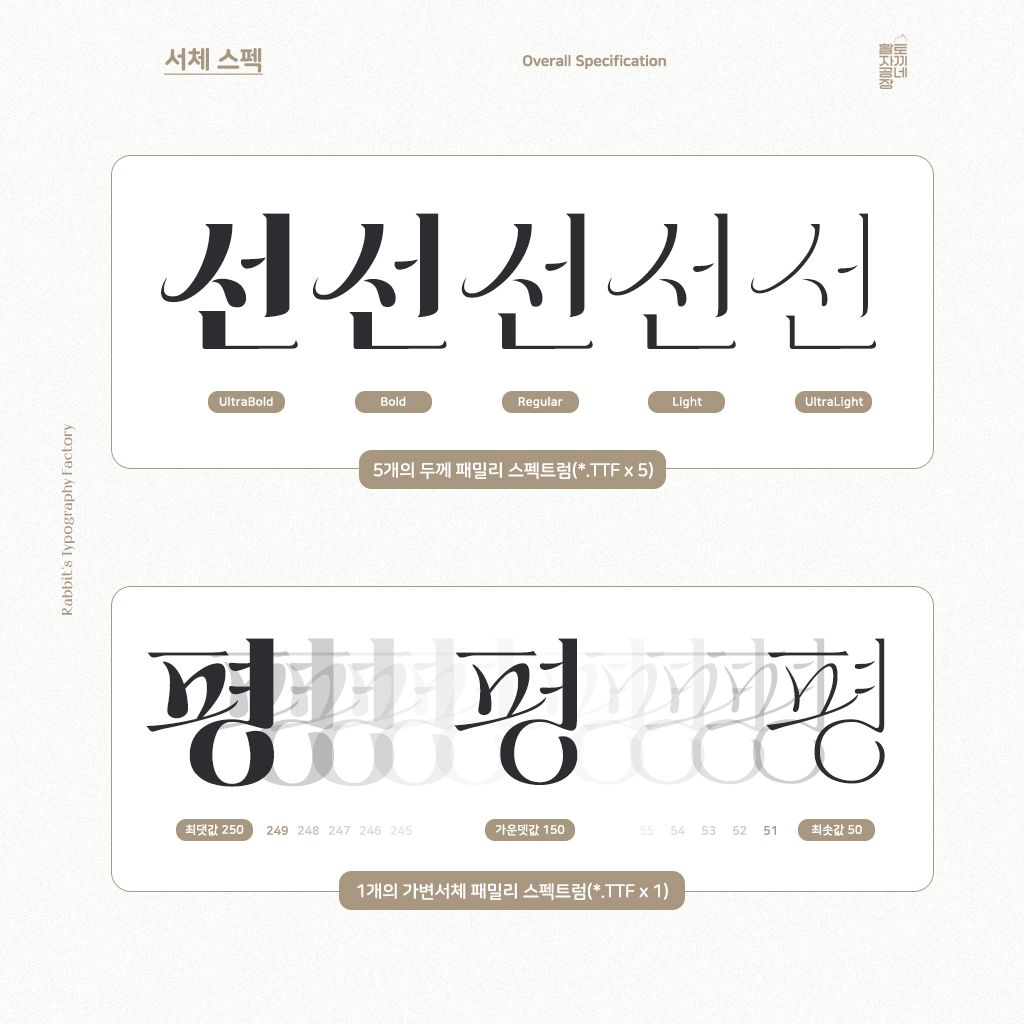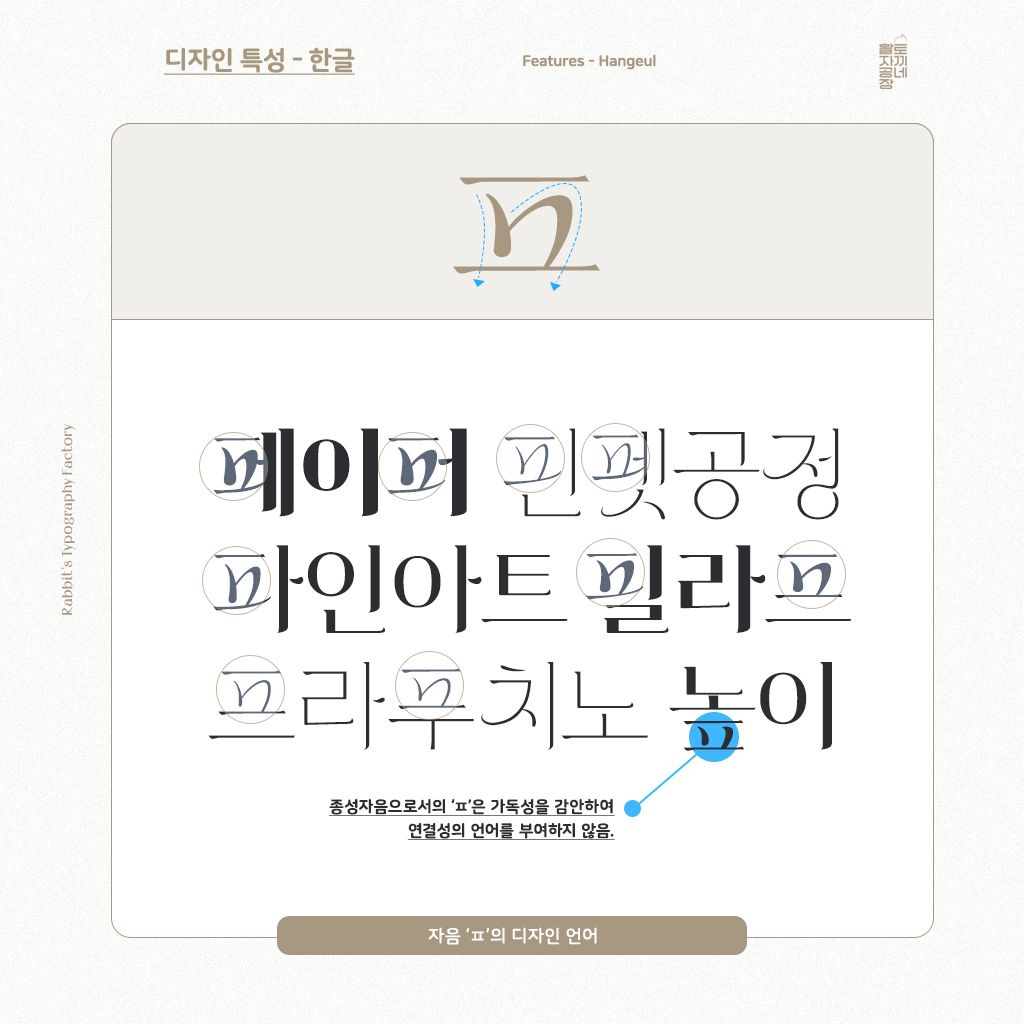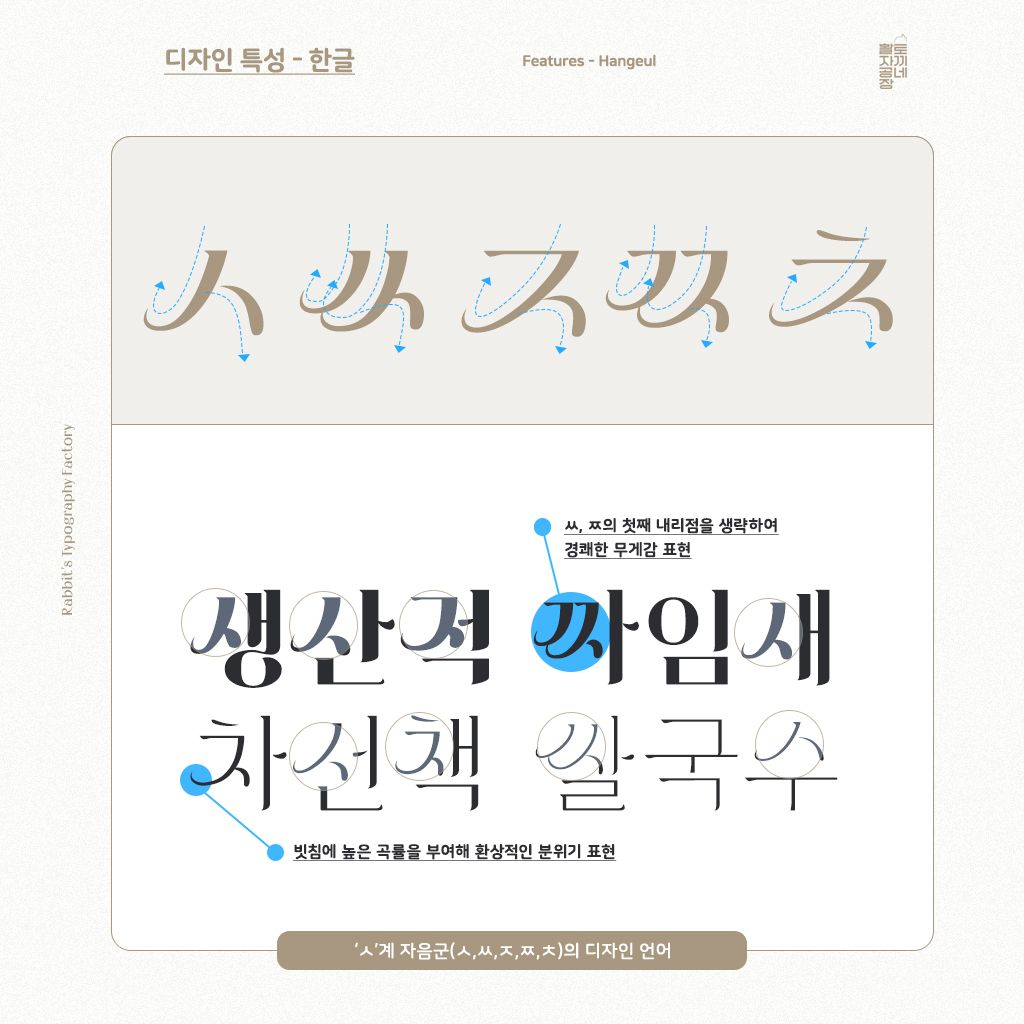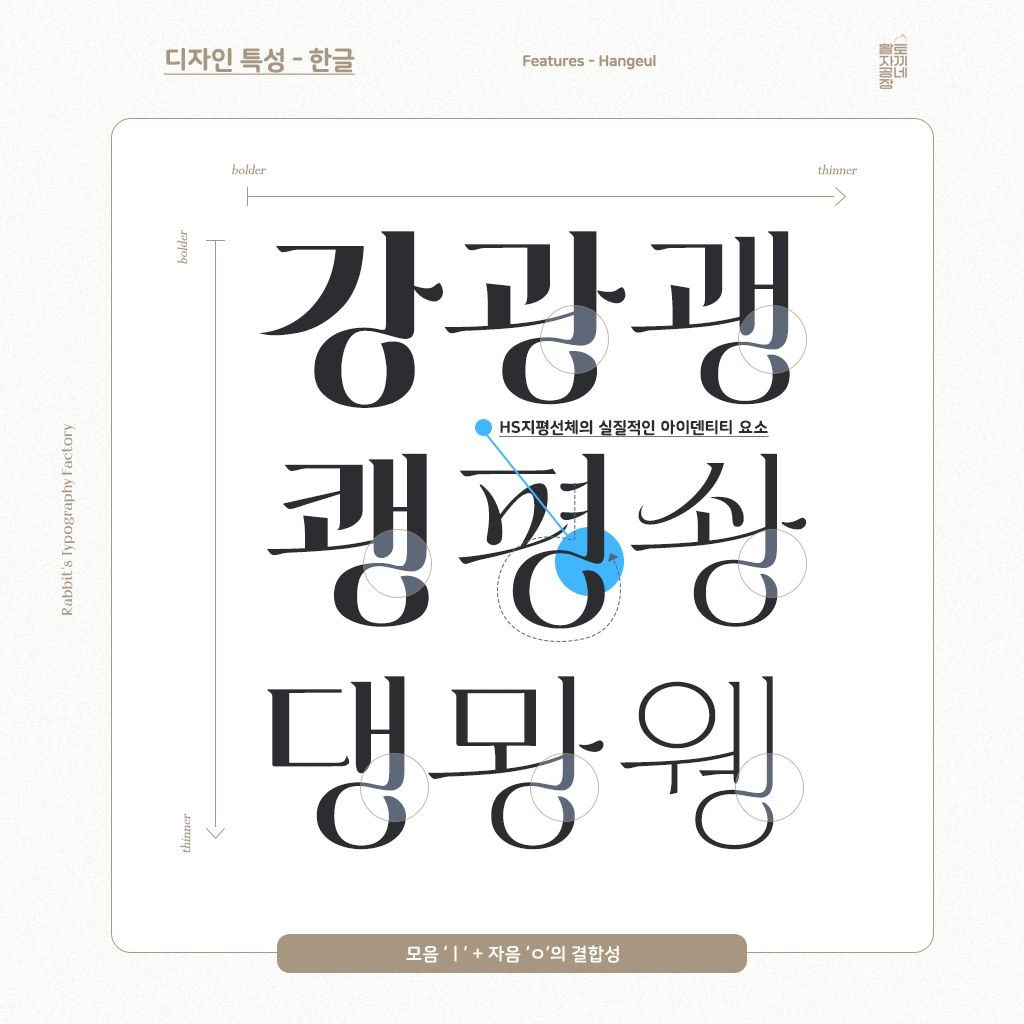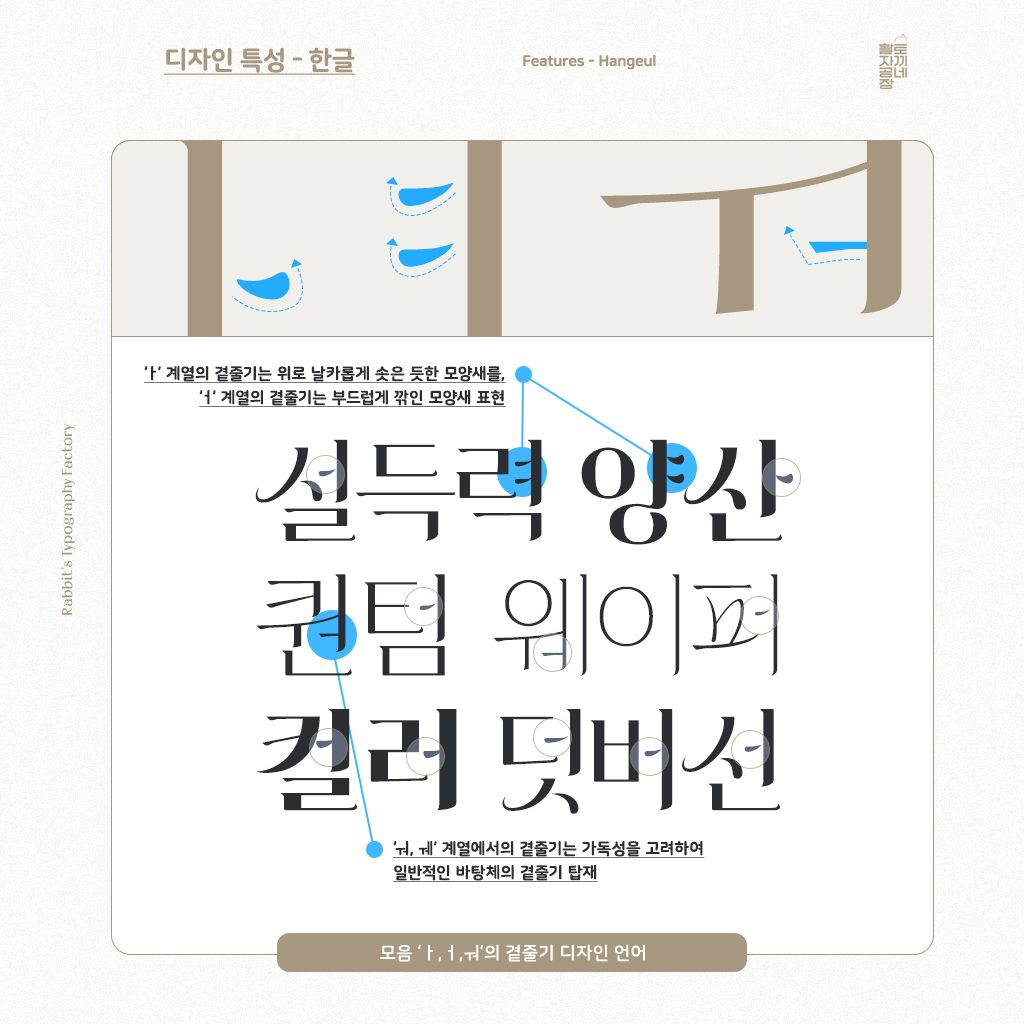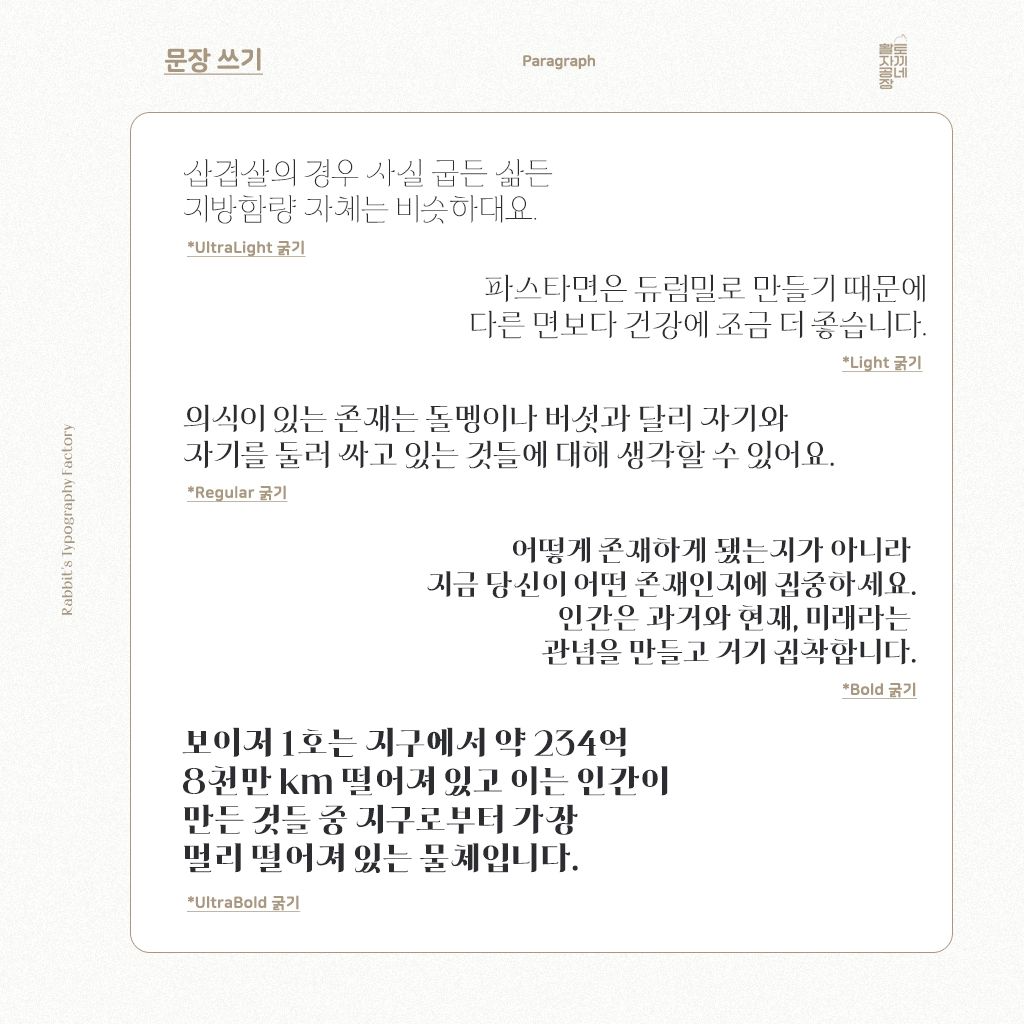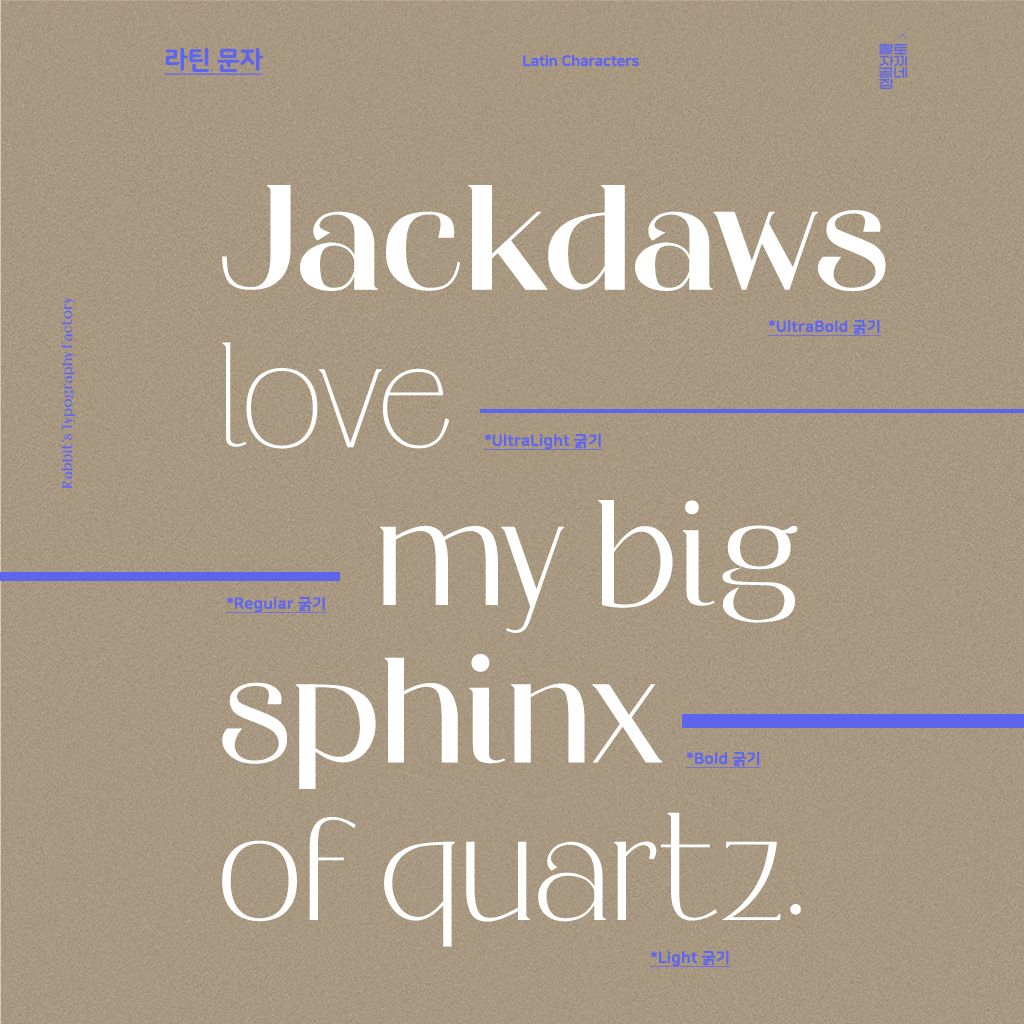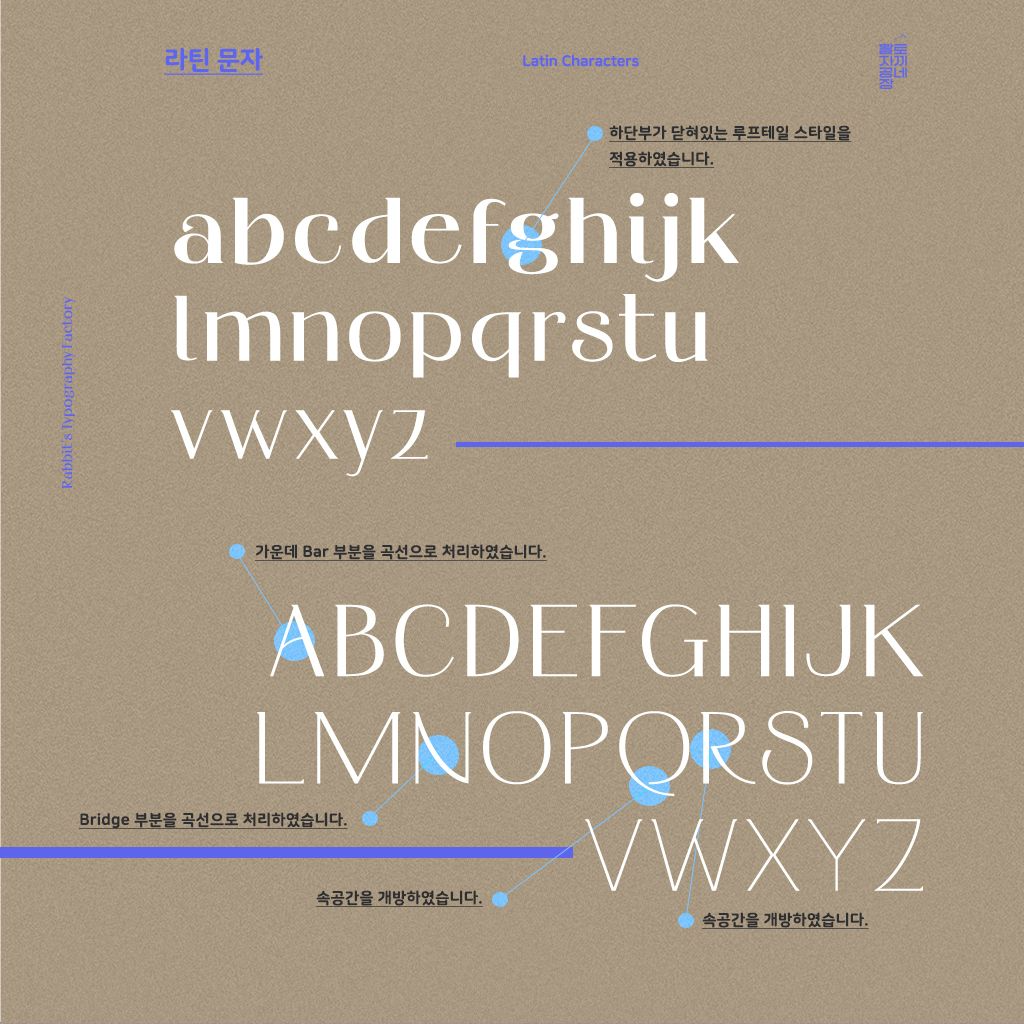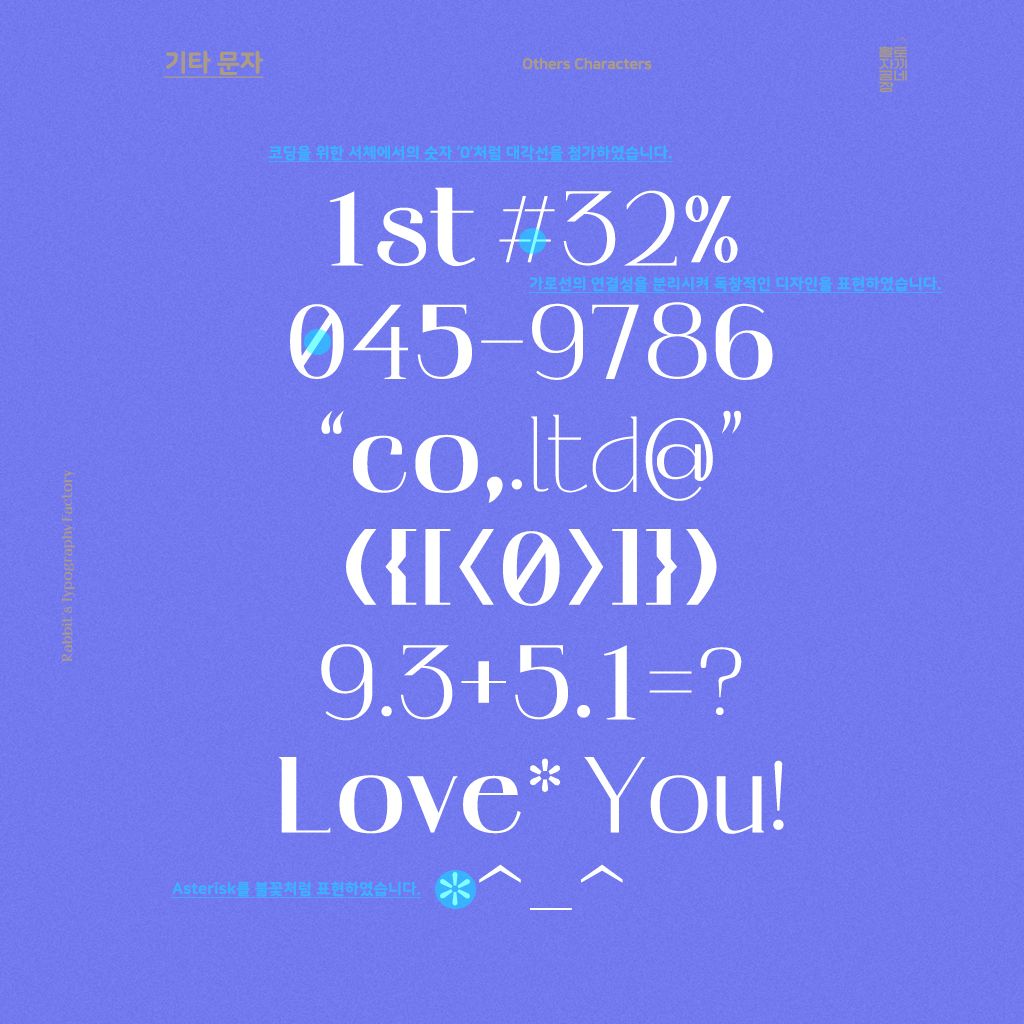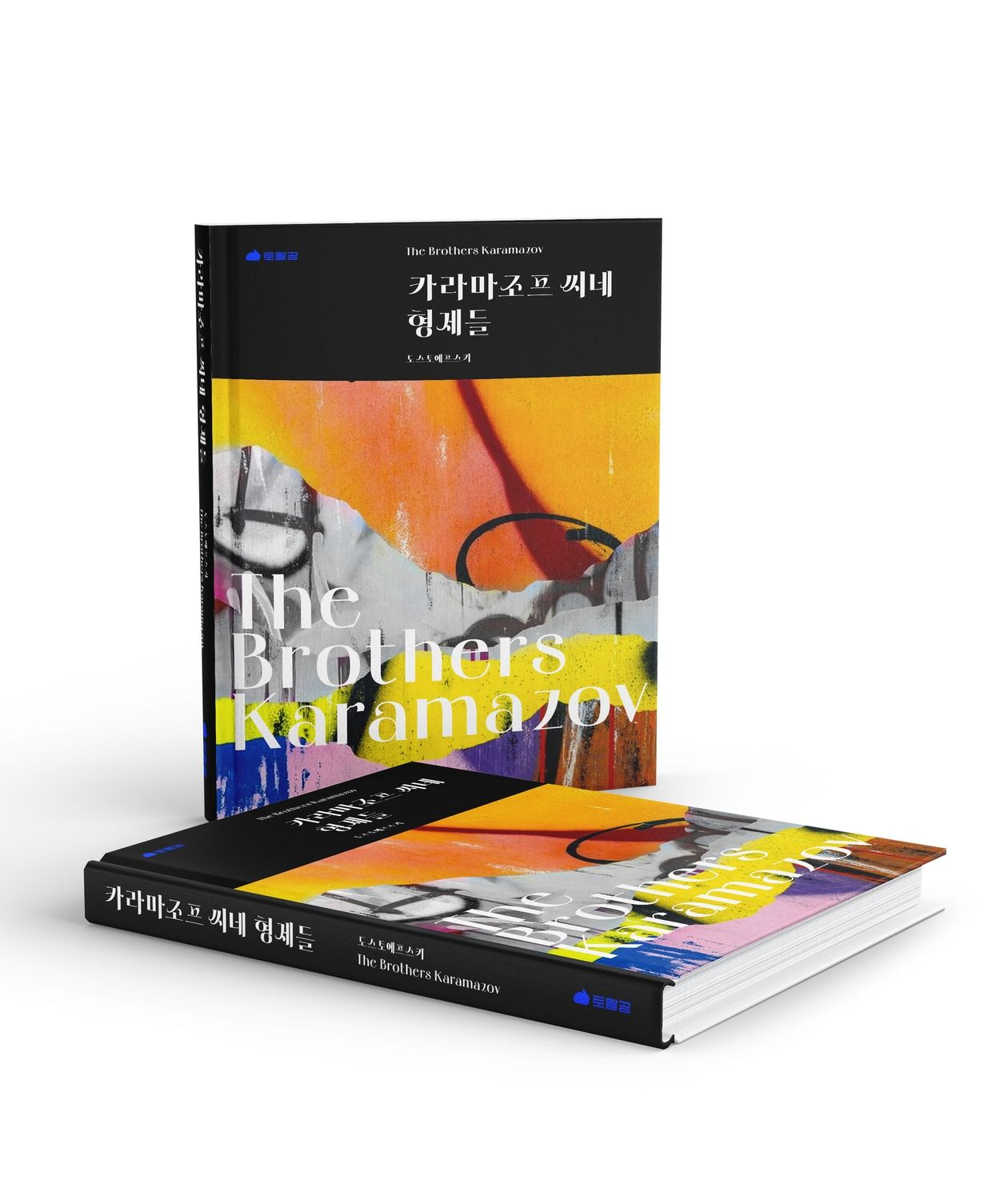
오로라 프로젝트의 첫 작품 HS지평선체(2023)
HS지평선체는 지난 8개월 동안 개발해오고 있는 한글 서체 작품이자, 토활공 역사상 최초로 VF(가변서체) 기술이 적용된 서체, 오로라 프로젝트 최초의 작품, 역대 두 번째로 펀딩에 의해 발행되는 서체 작품입니다.
가수 윤하의 중요 작품인 『사건의 지평선』에서 모티프를 얻은 작품으로써, 청각을 시각화하는 공감각화에 도전하는 기념비적인 작품입니다.
토활공 역사상 최초로 5굵기를 가진 한글 서체며, 가변서체 VF도 함께 발행됩니다.
이번에 기획하게 된 5굵기 서체는 별빛이 보여주는 연주운동의 항상성과 가변성의 특성이, 서체의 굵기 변화양상과 흡사하다는 점에서 착안해 표현한 것이며, 가변서체의 능동성은 이를 더욱 극적으로 보여줍니다.
HS지평선체